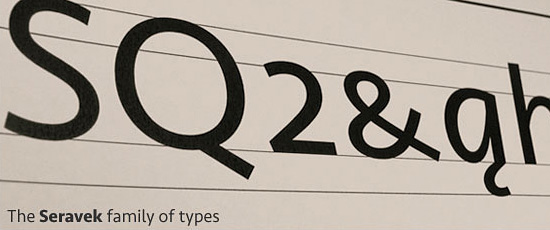
Seravek (Process Type Foundry)
Designed by Eric Olson 2003–2007
Seravek is a linear sans serif designed for identity, editorial
and information design. Five weights spanning Bold to Extra Light
with italics and small caps allow for a range of applications both
typographic and utilitarian in nature.
Eine schöne Schrift.
Nur ein Detail fällt mir auf. Der „Knick” beim Übergang vom Bogen zur Geraden bei manchen Kleinbuchstaben (n, m, u). Auch wenn ich das PDF stark vergrößere bleibt er (ist also keine Pixelgeschichte).
Ist doch komisch, oder?
jetzt wo du es sagst fällt es mir auch auf ...
kann ja aber eigentlich nur absicht sein oder?
diese stellen gefallen mir auch nicht gut. vor allem beim m kommt es mir merkwürdig vor, weil gleich zwei dieser übergänge auftauchen:
ich habe das pdf mal ausgedruckt, weil ich dachte, dass diese eigenheit vielleicht eine »optimierung« für print ist, deren sinn man in zeiten grassierender pdf-manie ohnehin hinterfragen könnte. sieht aber noch schlimmer aus. so schrecklich viel ist eric olson ohnehin nicht eingefallen, wie man erkennen kann, wenn man die seravek mal neben thesans bastelt (brandheißer schriftmischungstipp für anfänger!):
gut, es gibt nicht nur diese sieben buchstaben, es ist eine hübsche, gut ausgebaute opentype-schrift und dem fachmann ist sicher klar, welche welche ist – aber wer würde sich da die mühe machen, einem kunden zu erklären, dass er unbedingt die neue von processtype braucht? :twisted:
Die "TheSans" hat eine Neigung nach rechts (gut erkennbar am "o").
Der "Seravek" fehlt diese Eigenschaft. Sie ist "linearer" konstruiert .
Vielleicht ist es deshalb einfach nur logisch und konsequent, daß das "n" und weitere Buchstaben so aussehen wie sie aussehen. Trotzdem finde ich hätte man den Übergang harmonischer zeichnen können.
Das "a" gefällt mir bei der "Seravek" allerdings wesentlich besser als bei der "TheSans". Ich mag diese "Hängebauch-a"s nicht.
ich behaupte gewiss nicht, dass olson abgepaust hat. nur stellt sich bei der seravek für mich das kievit-feeling ein: einige buchstaben der thesans wurden mehr oder weniger übernommen, andere hingegen, die ich mag, zum beispiel die a-minuskel oder die j-majuskel in den aufrechten schnitten, durch formen ersetzt, bei denen ich an fago, eureka oder etwas ähnliches denken muss. auch wenn die neuen buchstaben einer einheitlichen konstruktion folgen, wirkt das ergebnis auf mich eher zusammengestückelt. wahrscheinlich sieht man darauf mit ganz anderen augen, wenn man die doch recht unmittelbaren einflüsse nicht kennt. ist auch mit ziemlicher sicherheit nicht zielführend, sich sowas vor augen zu halten – das gebe ich gerne zu.